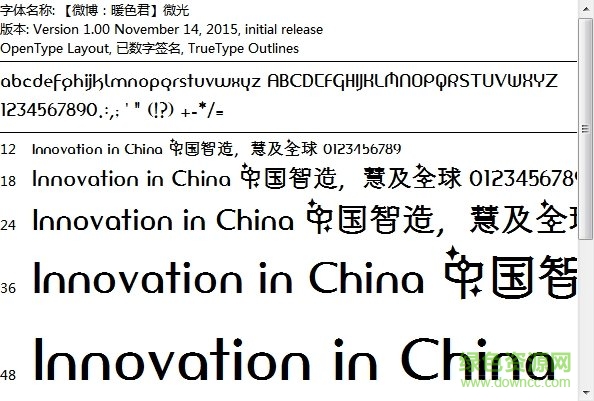
晨光熹微字体,又名暖色君微光字体,是一款样式圆润而别致的中文梳打字体,部分汉字进行了美化修饰,更显活泼生机,如果你很喜欢,绿色资源网即可免费体验哦!
晨光熹微字体又添加了图案进行装饰,设计精美,线条流畅,字型端正,整体效果十分出色。以广泛应用于横幅标语、美术设计、宣传海报、ppt、影视制作以及内容用字等领域。
晨光熹微体给人明亮而精简的外观,让文字拥有不一样的表达方式,字里行间的各种实心或空心字符都变得有灵性起来!